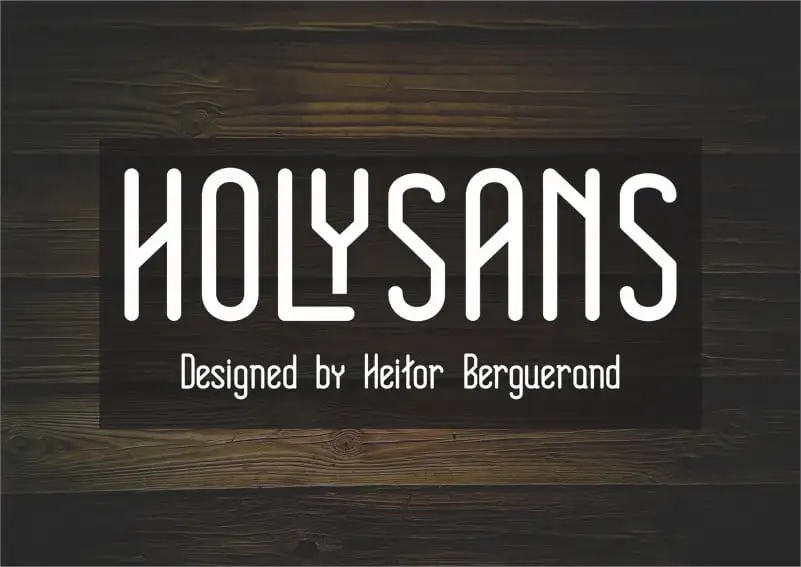
Holy Sans Serif Font – Download Grátis
Através de uma introdução revigorante ao universo das fontes de tipo abertas, anunciamos Holy Sans Serif Font – uma tipografia humanista sem serif que transmite a modernidade na estética do design gráfico. Esta fonte é perfeita para leitura de textos com múltiplos caracteres e estruturas complexas, bem como para criação de headlines dinâmicas e cativantes. Holy Sans Serif Font se destaca pela sua excelência em tipografia e composição, tornando-se uma escolha ideal para designers que buscam expressar elegância e modernidade em seus trabalhos visuais. Sua simplicidade e clareza são complementadas por um design equilibrado e sofisticado, fazendo de Holy Sans Serif Font um recurso indispensável para qualquer criador de conteúdo visual.